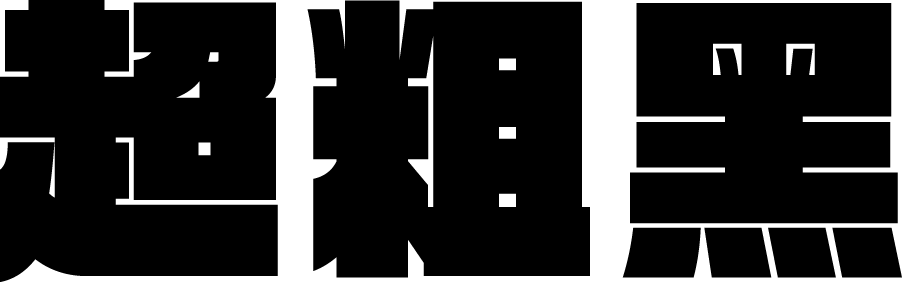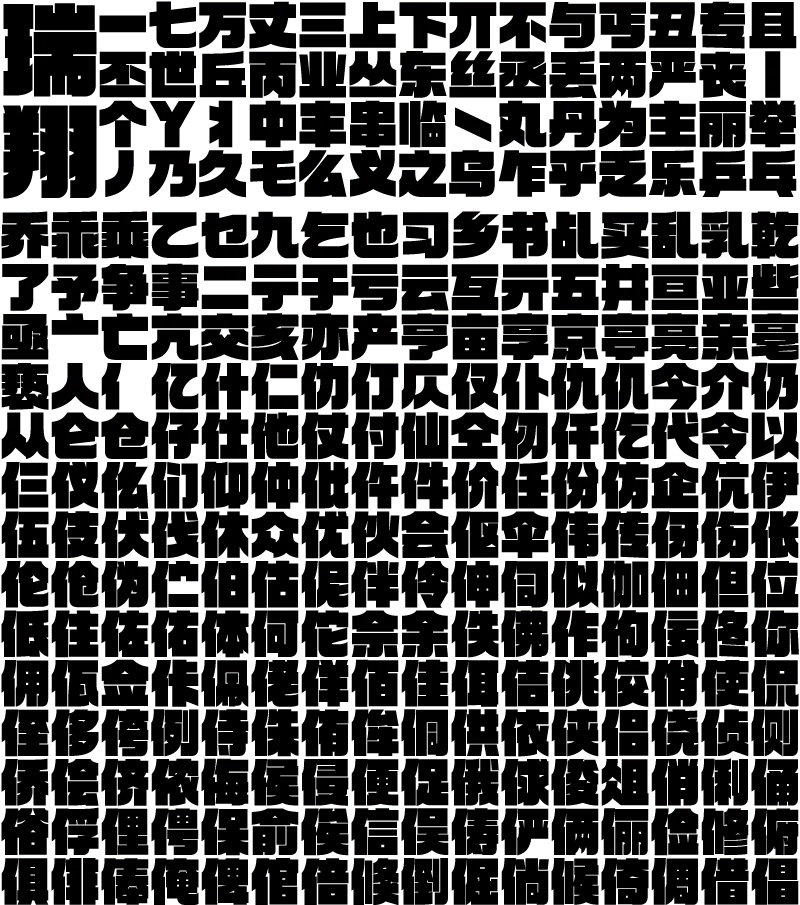
LOGO超粗黑の特徴
「LOGO超粗黑」は、「ロゴGブラック」のデザインをベースに生まれた中国語(簡体)書体です。『太く、強く、黒く』をコンセプトに、可読性とデザイン性の両面から「太さの限界」に挑戦して生まれた、究極の超極太ゴシック体です。文字を文字として認識できる限界まで画線を太くすることで、見る者を圧倒するほどの強烈なインパクトとオリジナリティを実現しました。
LOGO超粗黑-BK